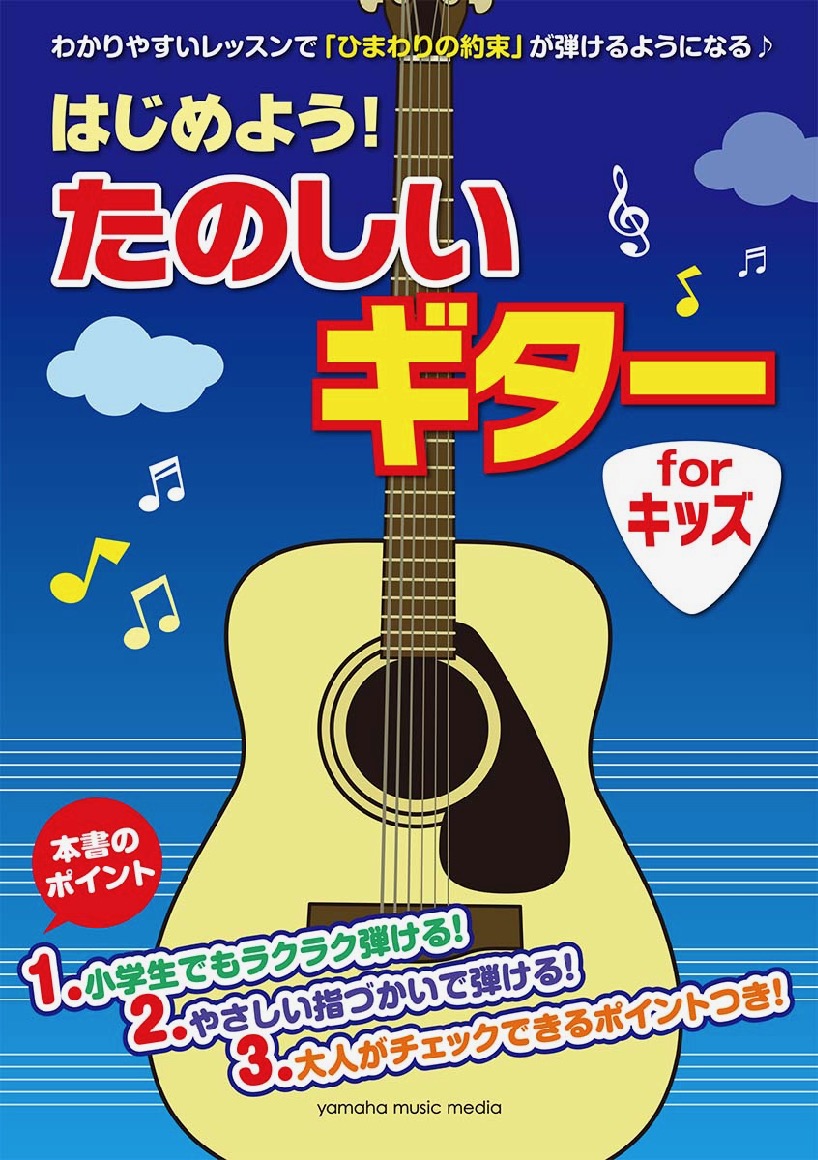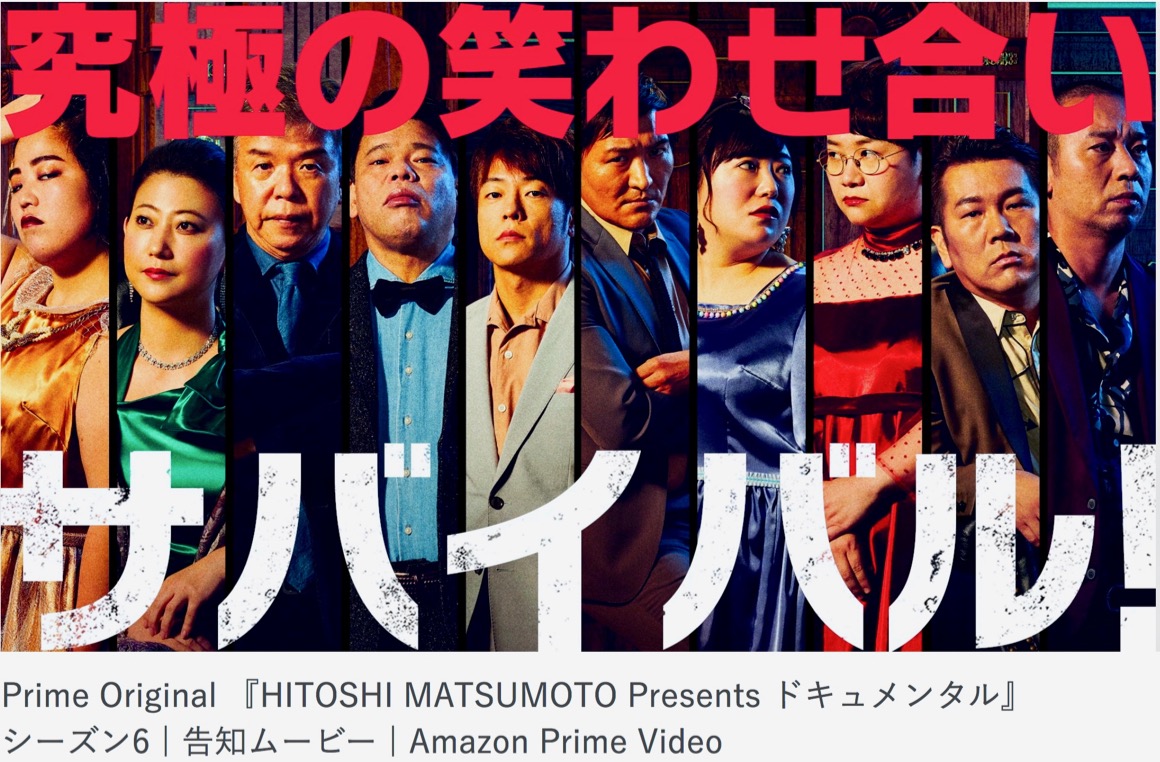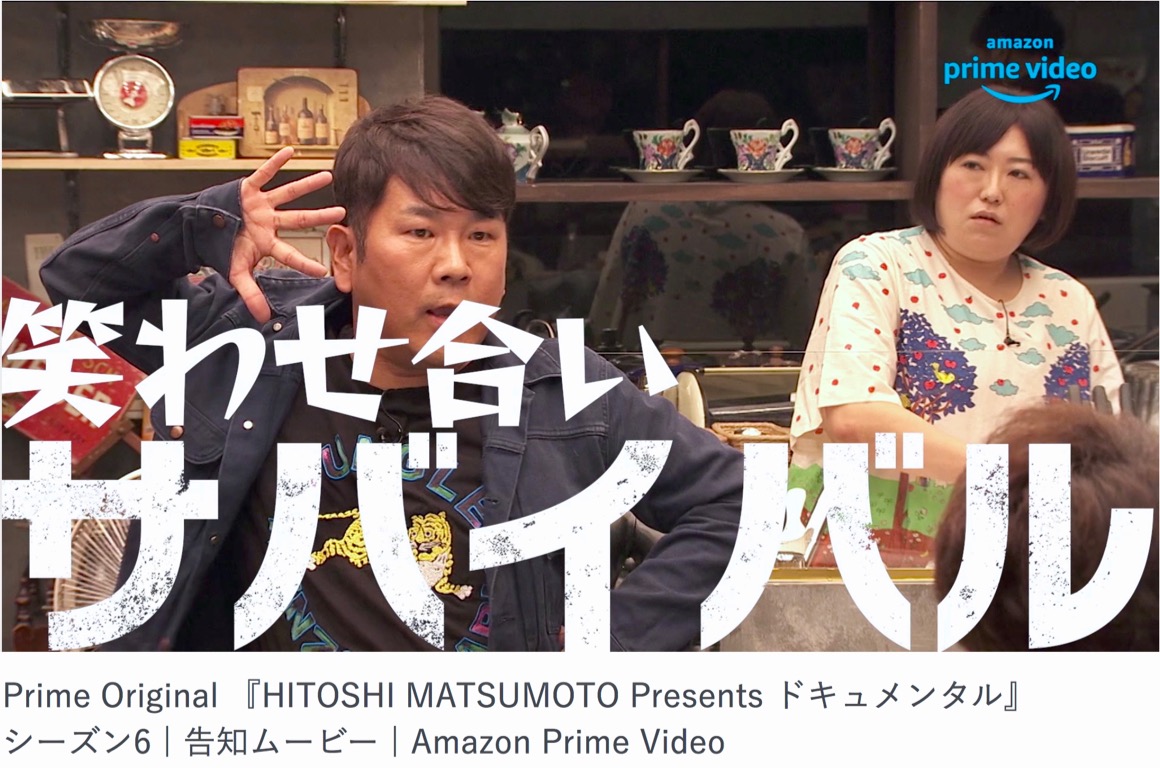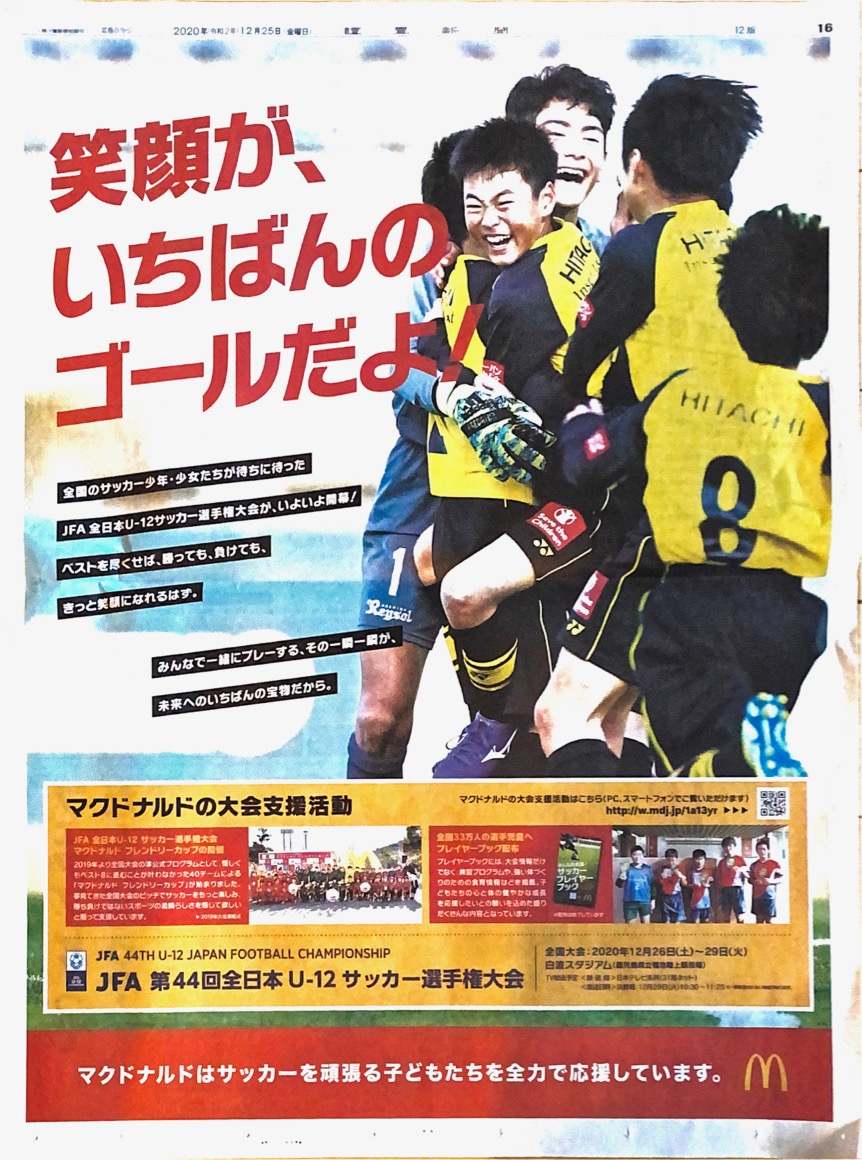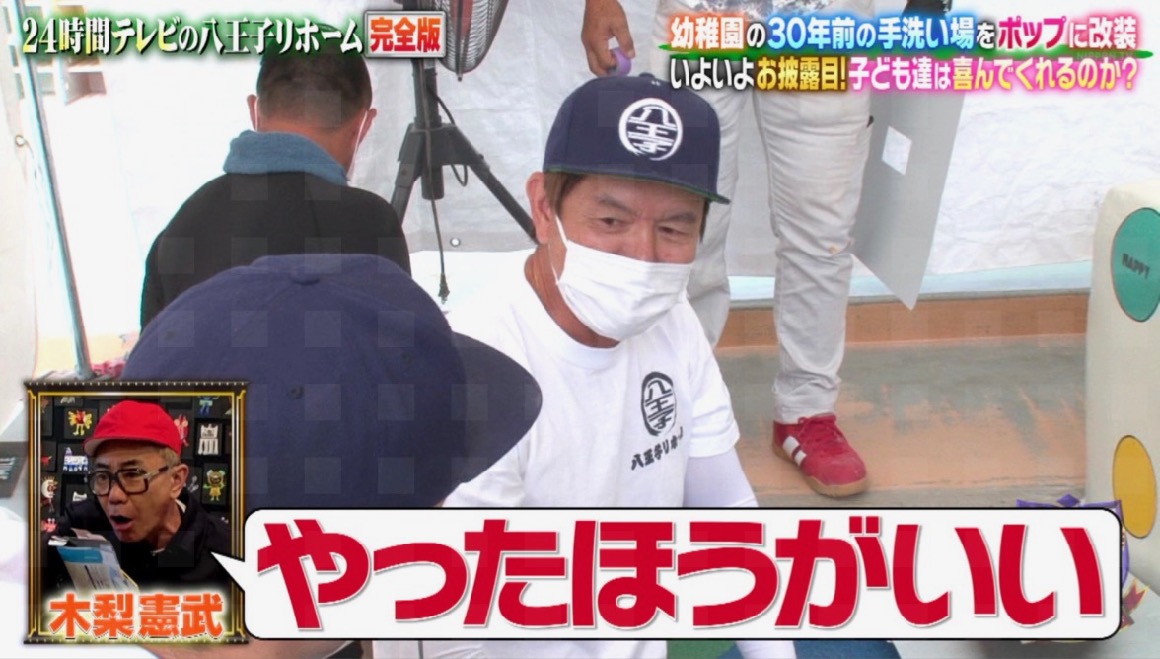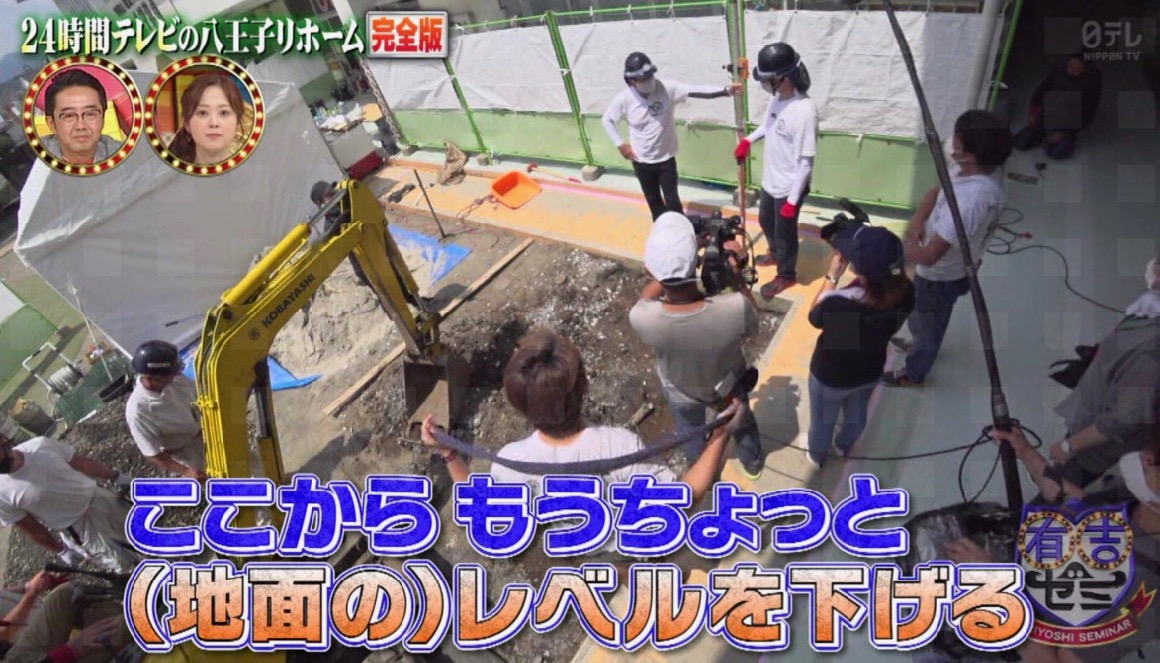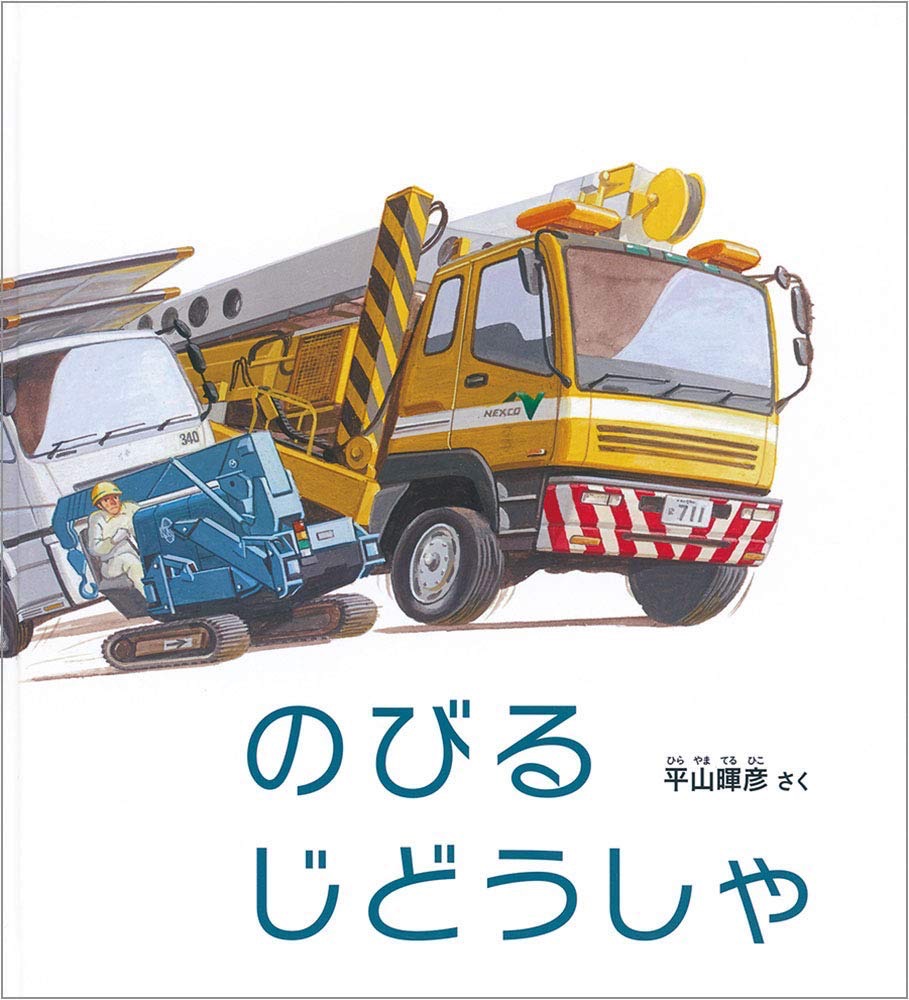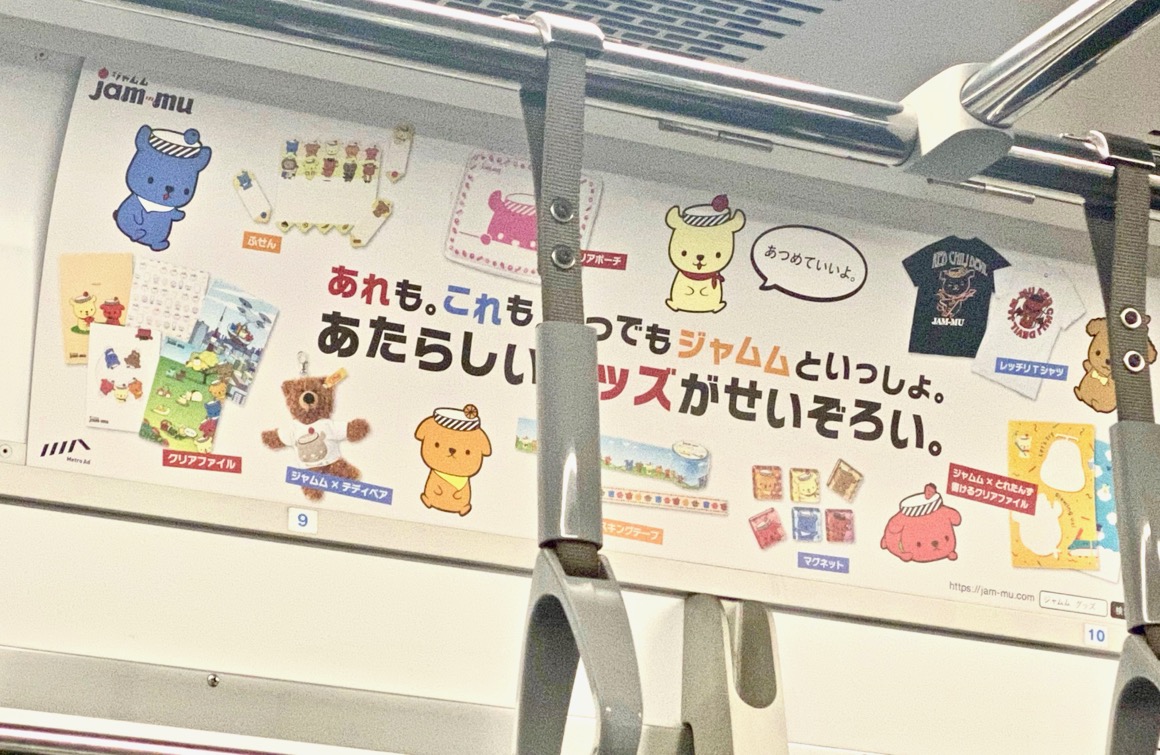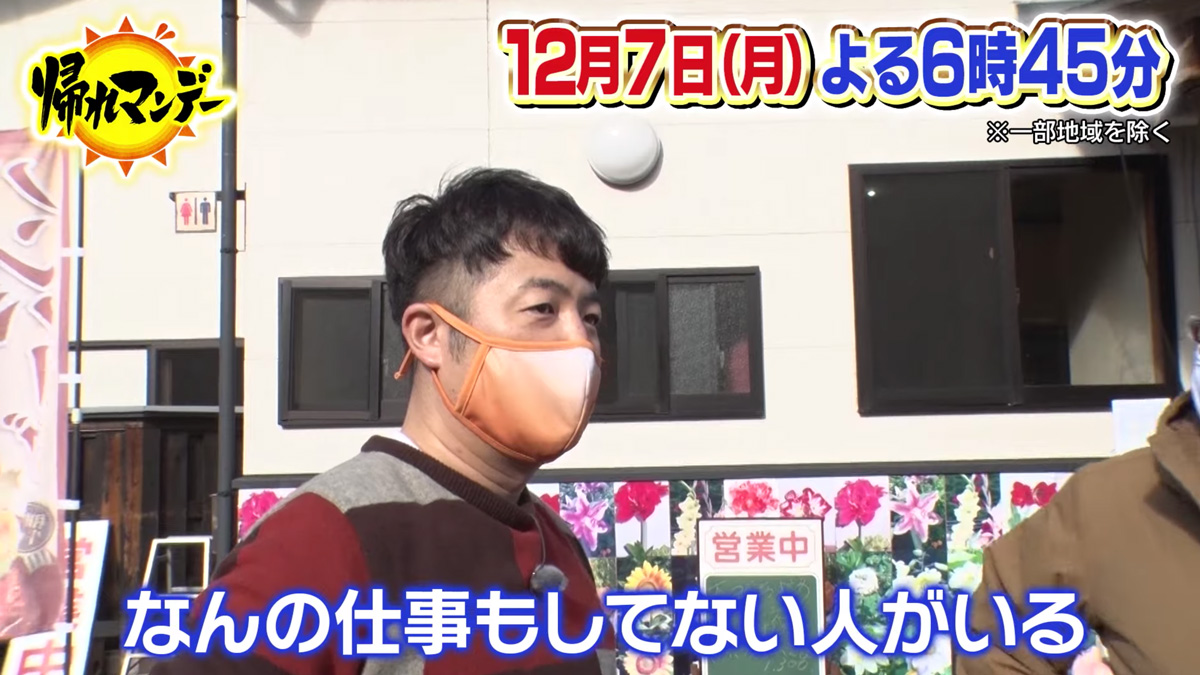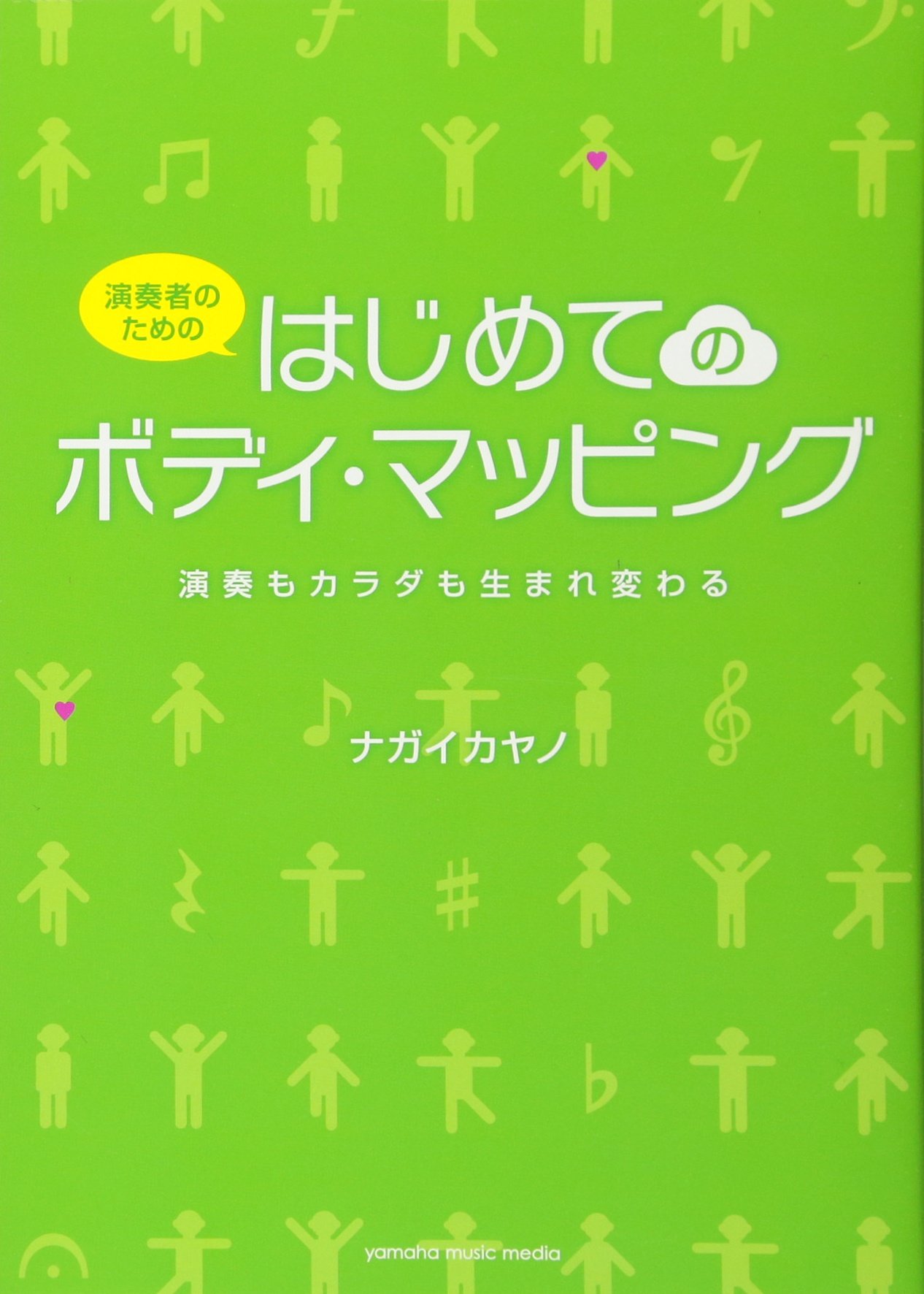
本の表紙  さとうゆたか  2021年12月22日(水) 14:38
書名:のぞいてみようクリスマス
著者:アナ・ミルボーン、エマ・アレン
発行:大日本絵
事件報道YTV  大阪のうめ吉  2021年12月21日(火) 9:46  Mail
大阪北新地の放火事件を報じる読売テレビ(YTV)の画面です。
ニタラゴルイカではなく、ライセンスされたもののようです。
恐竜のフイギュア  大阪のうめ吉  2021年12月20日(月) 4:19  Mail
タカラトミー発売
恐竜サウルスのフイギュアシリーズ
シリーズですからサウルス系のが他にも色々ありましたが自身のブログのザウルスちゃんを意識してステゴサウルスのみです。
平野区のショッピングセンター玩具売場で見つけたものです恐竜の名前の部分です。
ココちゃん通信 第164号  大阪のうめ吉  2021年12月18日(土) 7:59  Mail
SNSオピニオン日刊「ココちゃん通信」 12月18日第164号 上半分
トップ見出しにニタラゴルイカを使用。
その下は あられ
縦見出し ルイカ キャピレラ
リード キャピレラ
中央見出し ニタラゴレラ
写真説明 キャピレラ
下部分です  大阪のうめ吉  2021年12月18日(土) 8:04  Mail [修正]
同日付下半分です。
縦見出し えれがんと平成明朝
囲み 本文 わんぱくレラ
下 レラ あられ わんぱくレラ
※えれがんと平成明朝の見出しはかなを使わない漢字のみにしています。
タイプラボのフォントだけで新聞が構成されてるんですね。
新聞記事  大阪のうめ吉  2021年12月17日(金) 15:40  Mail
日数が経過していますが、大阪市内なのですが、そちらの方面に出向いたさい北日本新聞社大阪支社の看板を見つけて入手してきたものです。
富山県で発行されている「北日本新聞」10月21日に掲載された富山県のマイナンバーカードを周知・啓発する記事下広告です。タイプラボさんが手がけたものです。モリサワさんの「タイプラボN」のようです。
ポケモン最新作  takumi  2021年12月7日(火) 22:55  HP
Nintendo Switchのゲームソフト「ポケットモンスター ブリリアントダイヤモンド・シャイニングパール」の商品パッケージで使われていたニタラゴフォントです。
何年も前からポケモンシリーズでは、販促媒体やゲーム作中などでニタラゴを使っています。
これはゲームの作中より。
もう1枚。
任天堂には、F社がこのフォントをライセンスしてますから、たくさん使われてますね…。
Adobeフォントのサイトにて  匿名  2021年11月14日(日) 8:50
AdobeFontsのフォント検索画面にて、ニタラゴと思われるものを発見しました。
「かな書体」の分類のボタンとなっているので、おそらくモリサワの「タイプラボN」だと
サイト内では、SVG(http://www.w3.org/2000/svg)化されているので、タイプラボフォントが提供される前からあると思います。
動画のタイトル  さとうゆたか  2021年11月12日(金) 8:31
こどもの詩「あんたのせいだよ/コロナに負けるな!」
モバイルオーダー  さとうゆたか  2021年11月4日(木) 8:31
マクドナルドの広告画像。
テレビ番組  さとうゆたか  2021年10月24日(日) 16:21
テレ朝系の「しくじり先生 俺みたいになるな!!」。
もうひとつ。